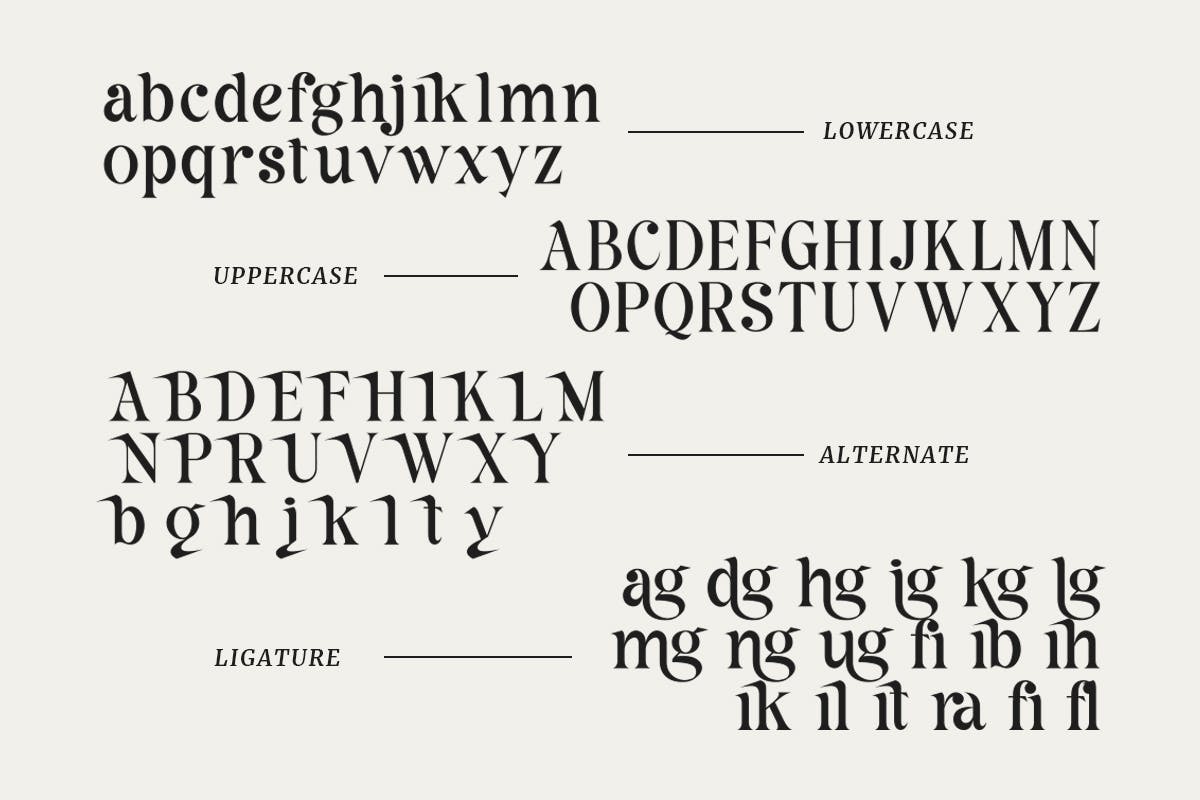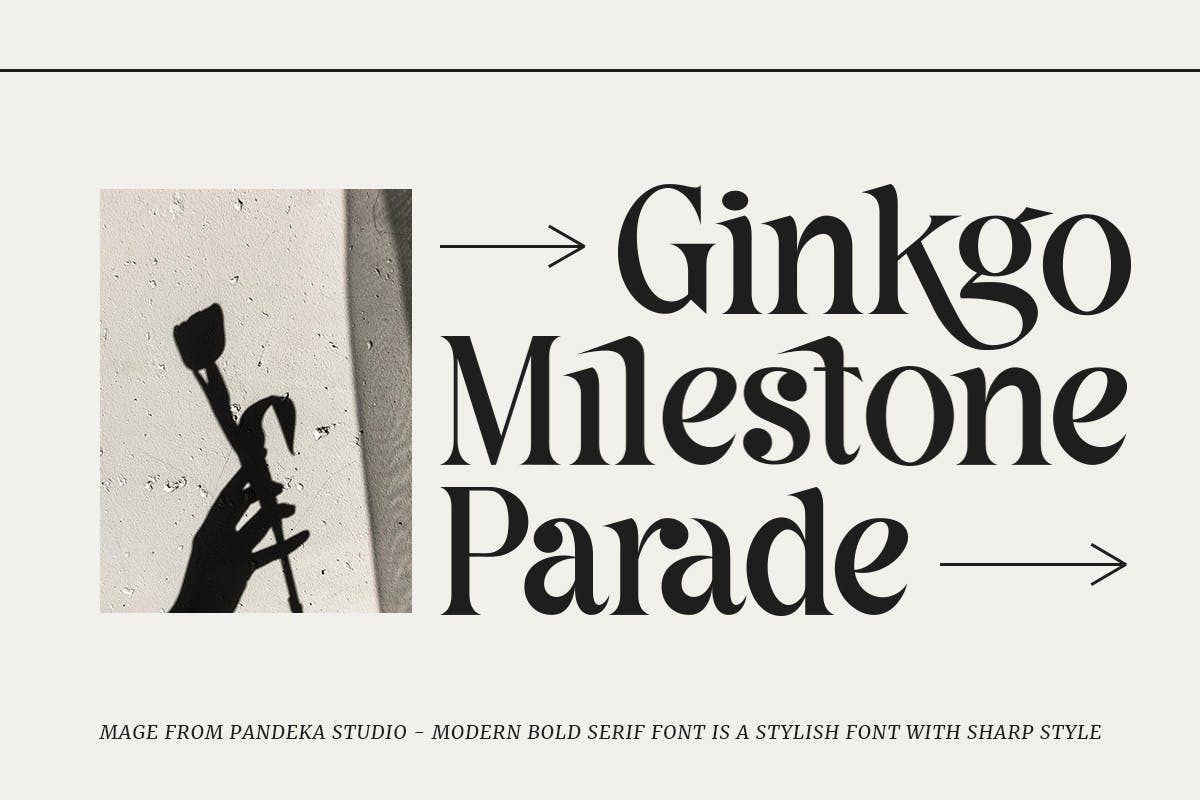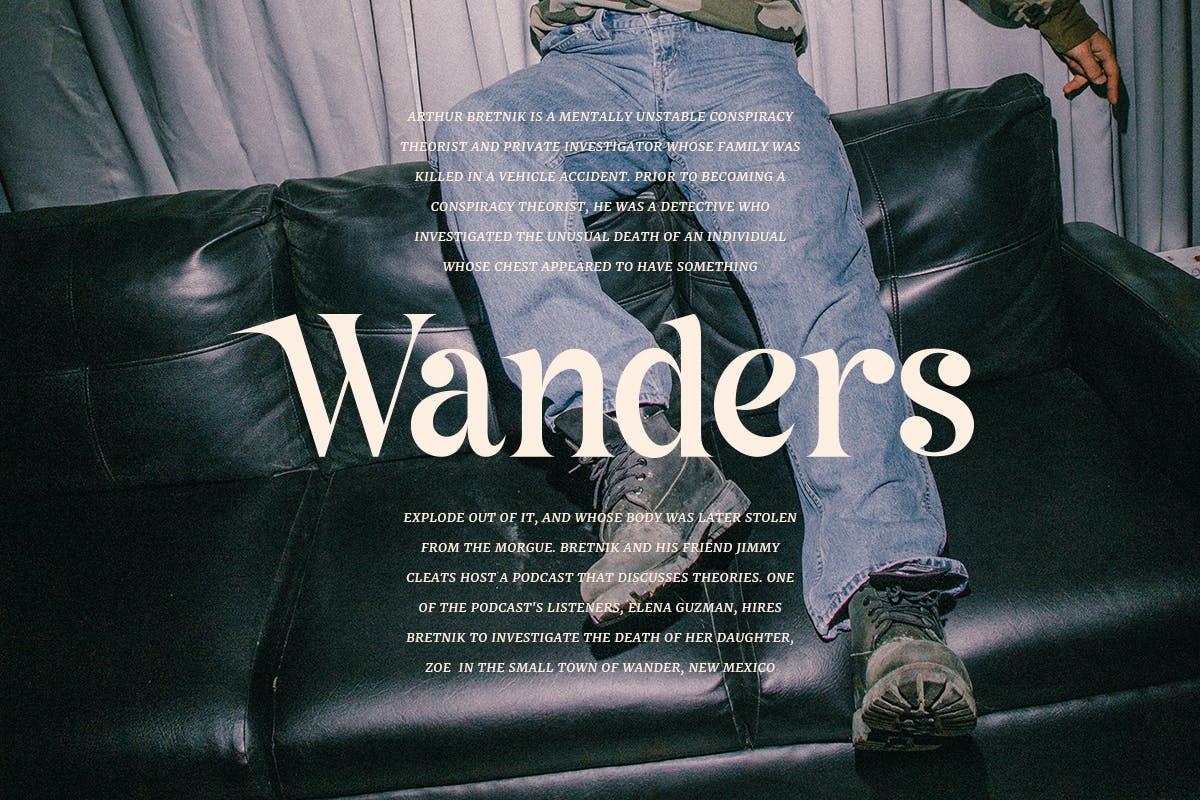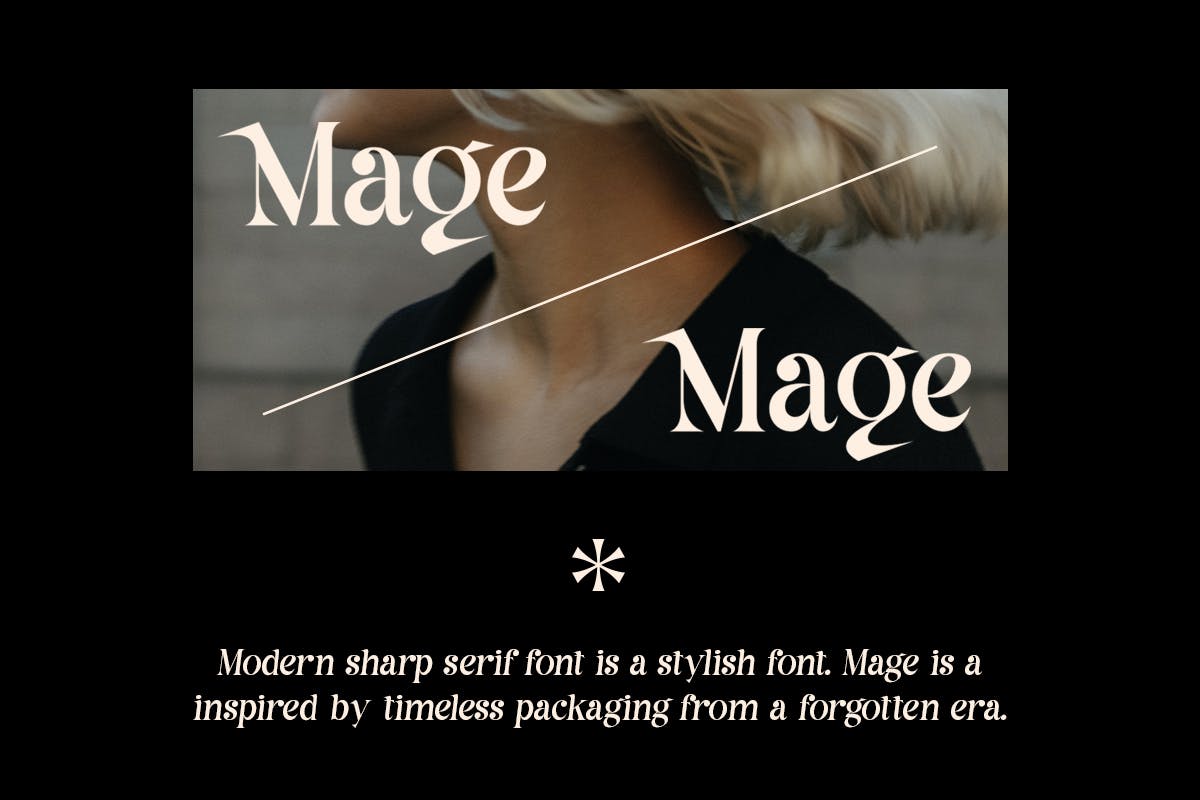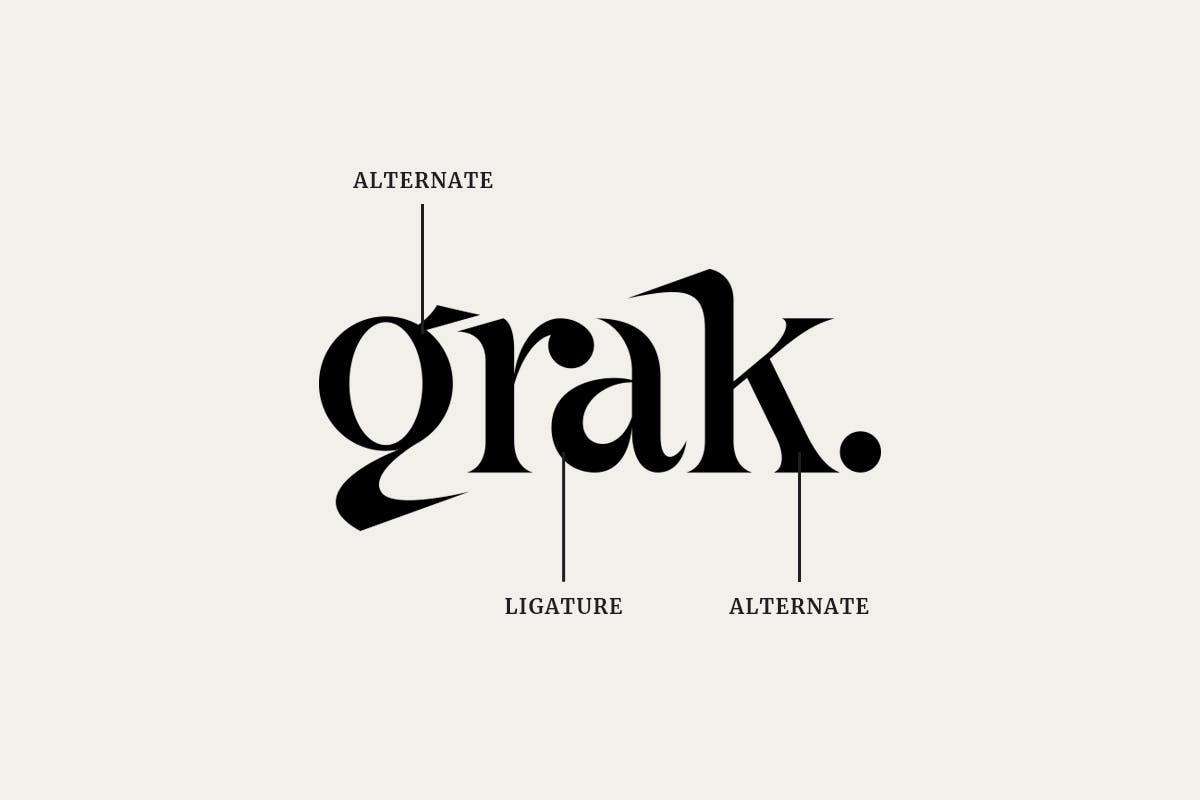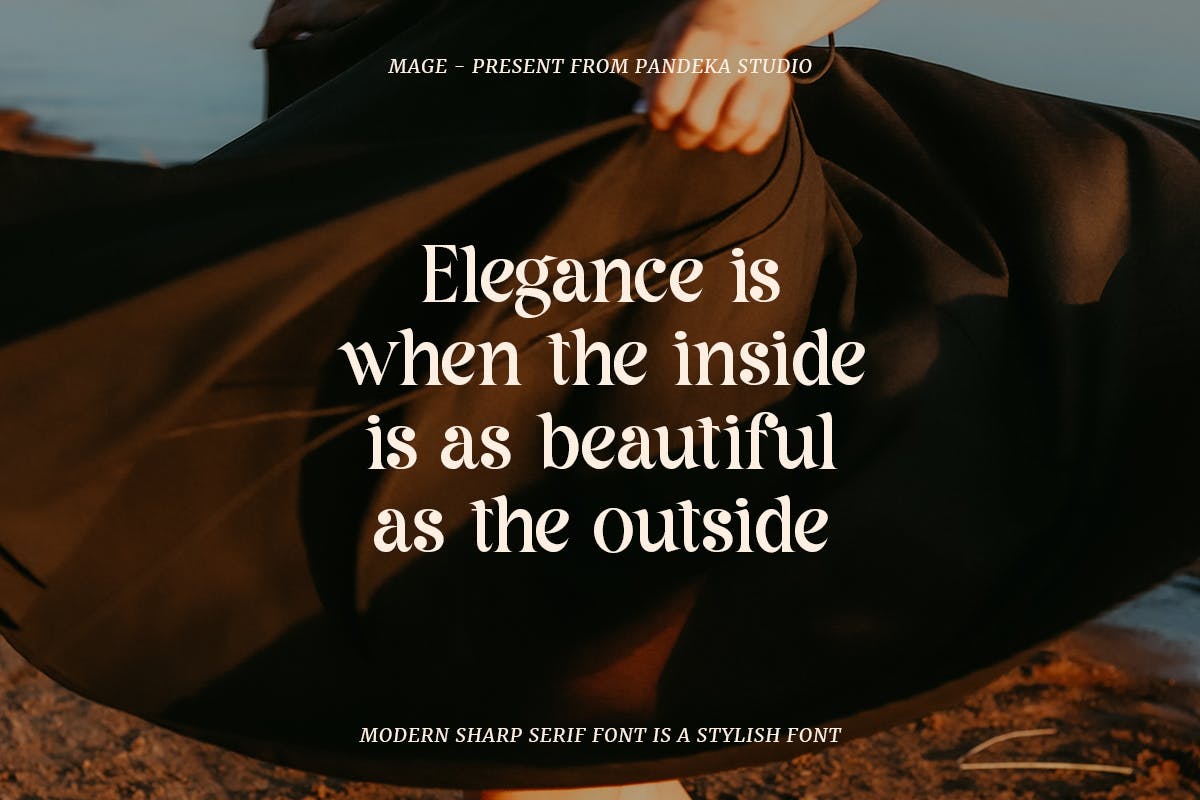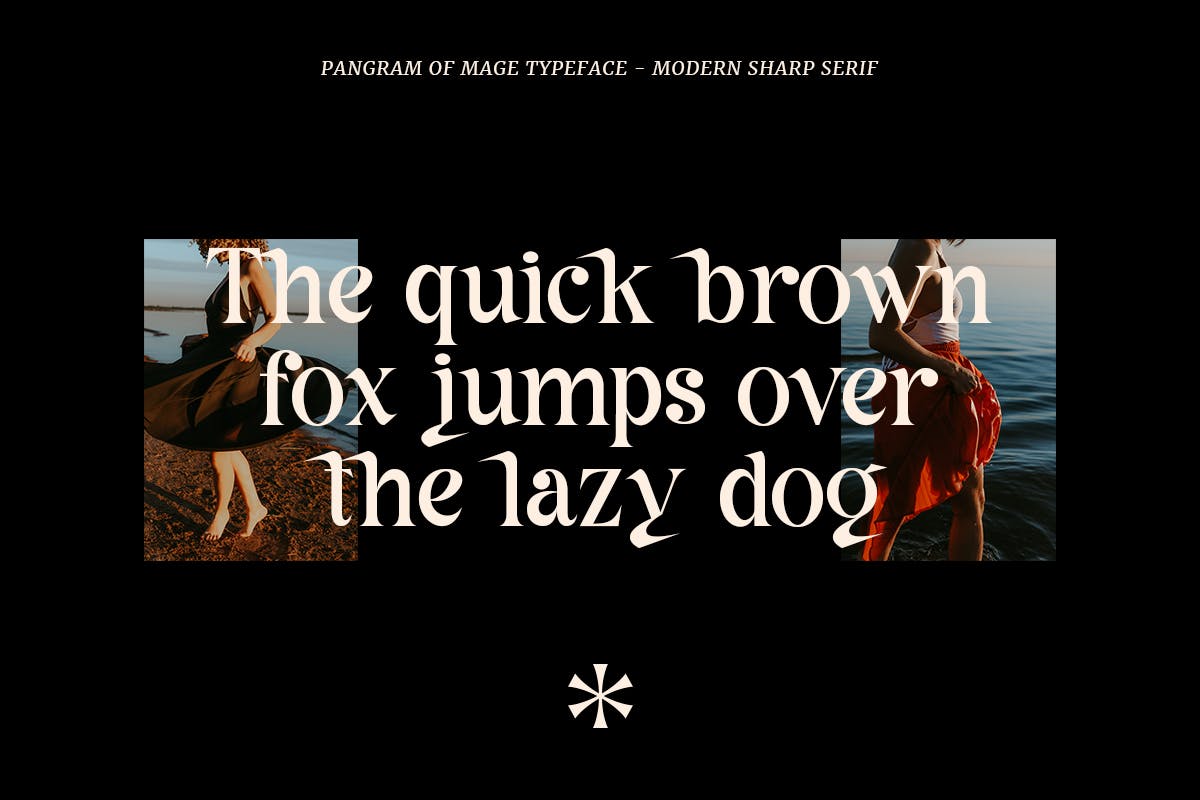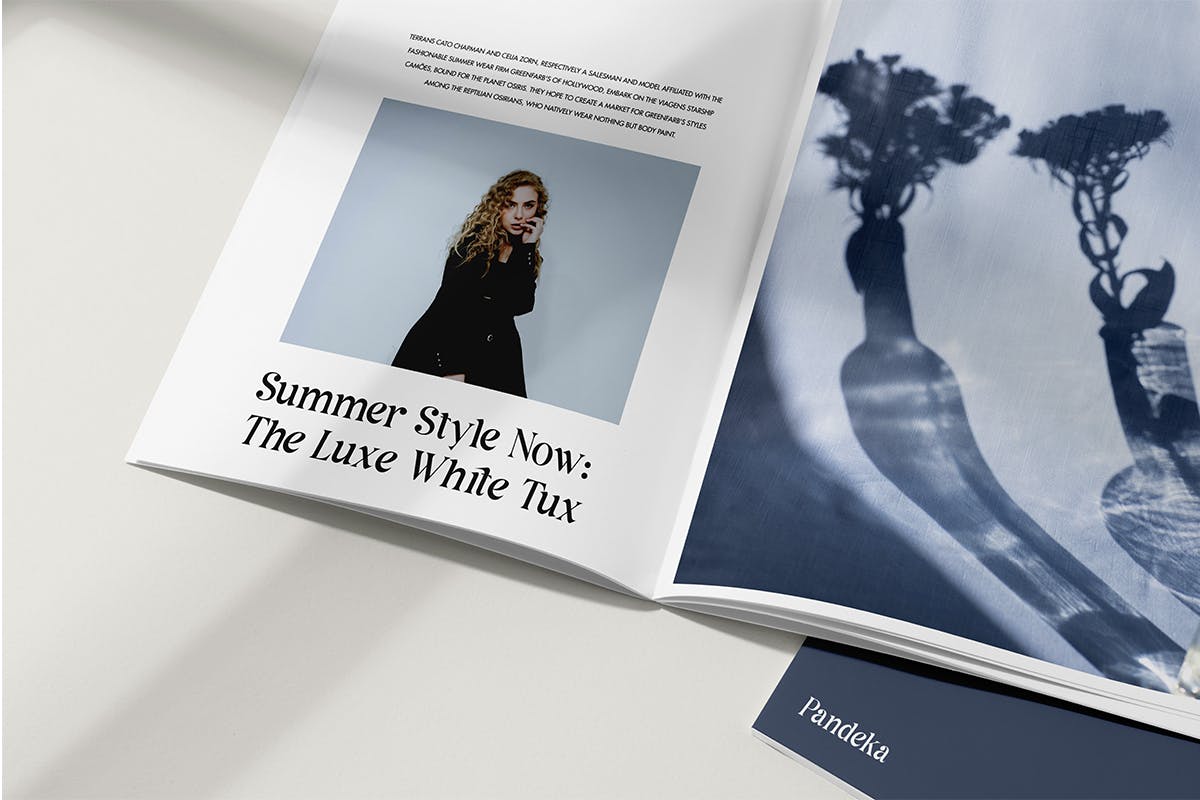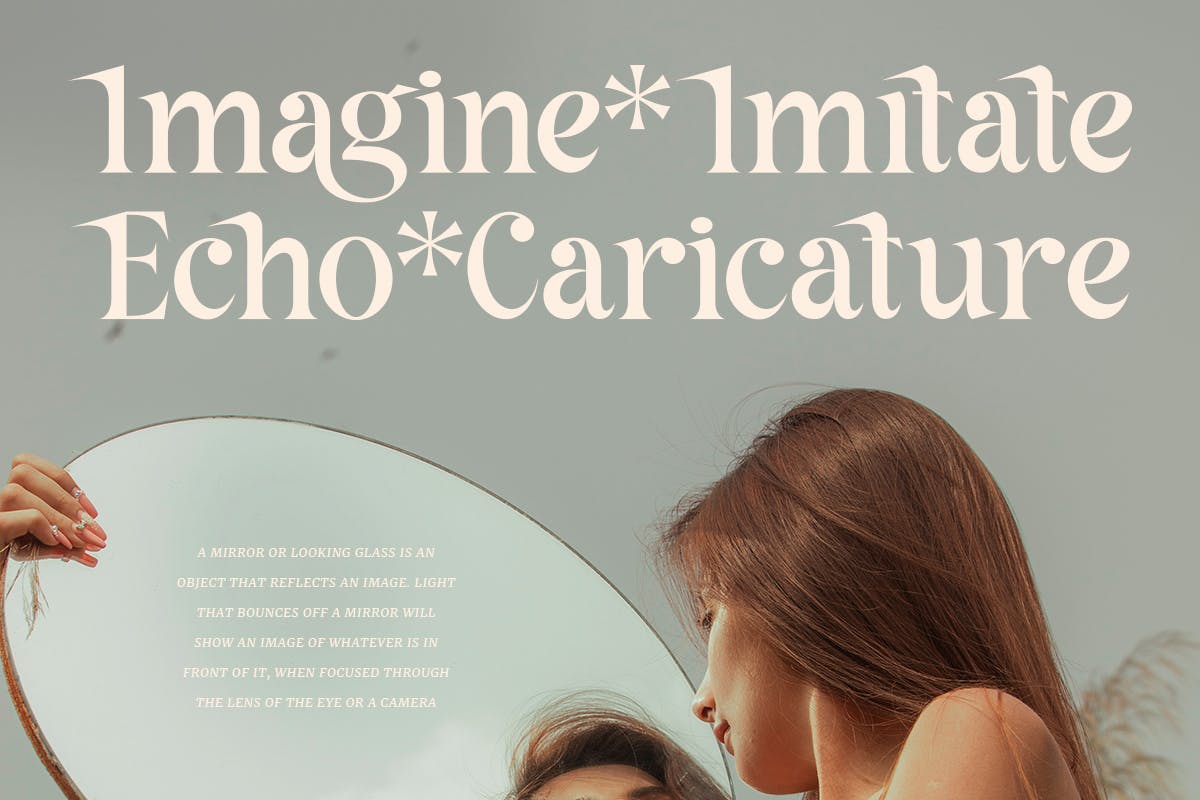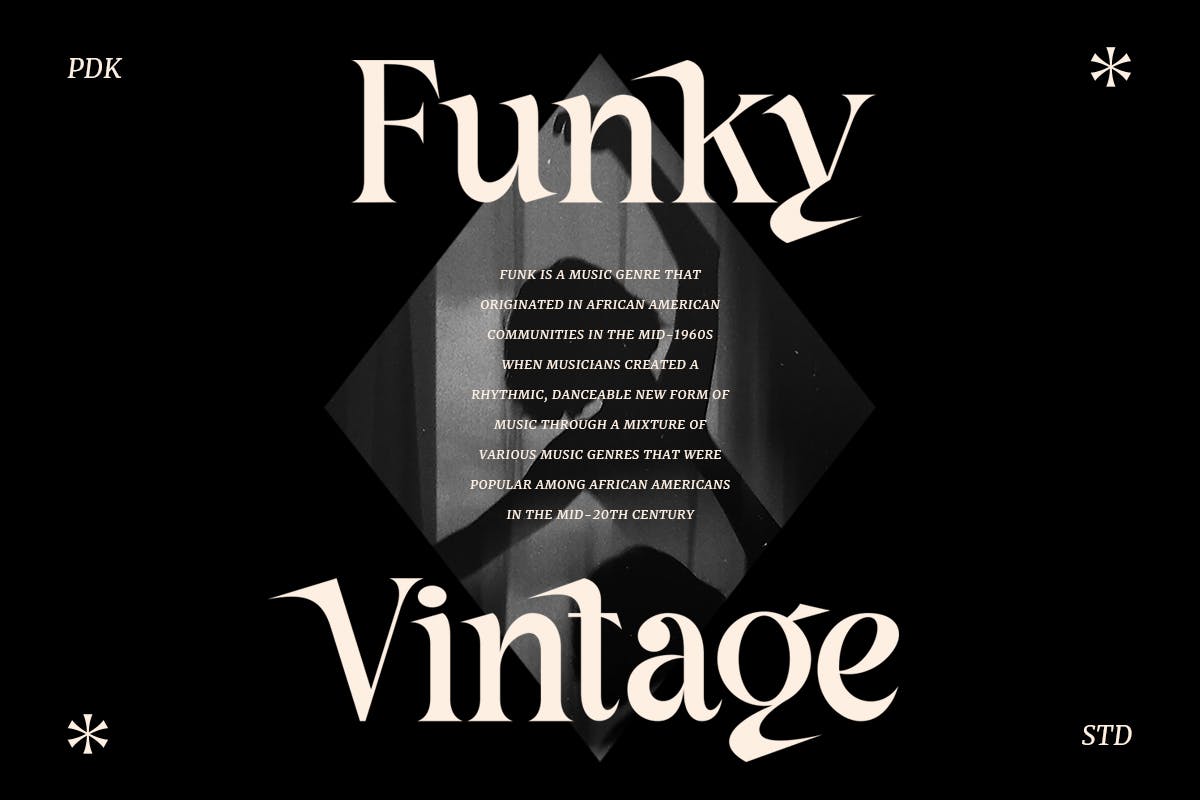
معرفی فونت جدید و تیز، مِیج!
مِیج - یک نوع فونت سریف با طراحی تجربی و تیز است. این فونت از بستهبندیهای جاودانه از یک دوران فراموششده الهام گرفته است. مجموعهای زیبا از جایگزینهای سبک با کاراکترهای منحصر به فرد دارد.
مِیج - یک فونت بیباک و شیک که برای عناوین بزرگ در هر دو رسانه چاپی و وب مناسب است. این فونت با سبک ایتالیک، حروف بزرگ و کوچک منحصر به فرد و همچنین اعداد، علائم نگارشی و حروف چند زبانه ارائه میشود.